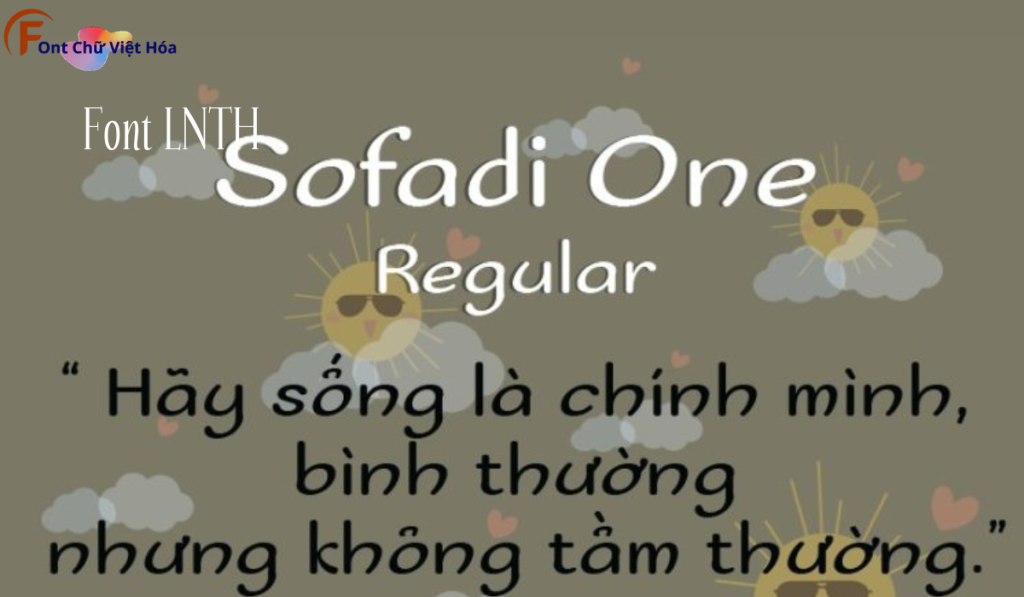
Font LNTH Sofadi One Việt Hóa
Font LNTH Sofadi One Việt Hóa là một font chữ thân thiện, thuộc bộ LNTH, với thiết kế mềm mại và dễ đọc. Phong cách của font này phù hợp với các dự án thiết kế cần sự thân thiện và dễ tiếp cận, như poster, thiệp mời, hoặc bảng hiệu. Font LNTH Sofadi One Việt Hóa mang đến sự thân thiện và dễ nhận diện, ứng dụng trong các lĩnh vực sáng tạo. Đặc điểm hình dạng của font bao gồm các đường nét mềm mại và dễ đọc, giúp tăng tính thẩm mỹ và sự chú ý. Việc Việt hóa font giúp người dùng dễ dàng sử dụng trong các thiết kế tiếng Việt, mang lại sự tiện lợi và linh hoạt.